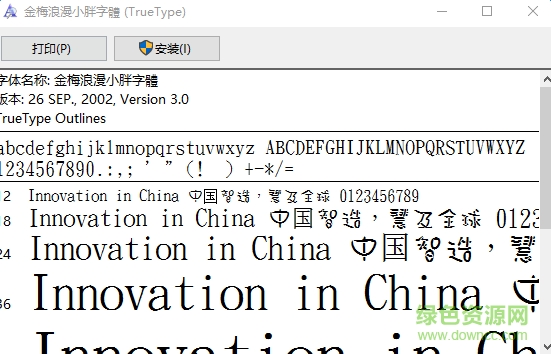
金梅浪漫小胖
金梅浪漫小胖字體是金梅字庫(kù)中很有個(gè)性的一款電腦字體,而且這款字體寫(xiě)出來(lái)的字是很好看的,字形美觀、大氣,具有自己獨(dú)特的魅力,喜歡的朋友可以來(lái)綠色資源網(wǎng)下載。
金梅浪漫小胖字體是一款很不錯(cuò)的電腦字體,它是具有藝術(shù)特點(diǎn)的,因此寫(xiě)出來(lái)的字也是很美的, 用于廣告設(shè)計(jì)、藝術(shù)設(shè)計(jì)等方面都是再合適不過(guò)了,歡迎大家來(lái)綠色資源網(wǎng)下載。